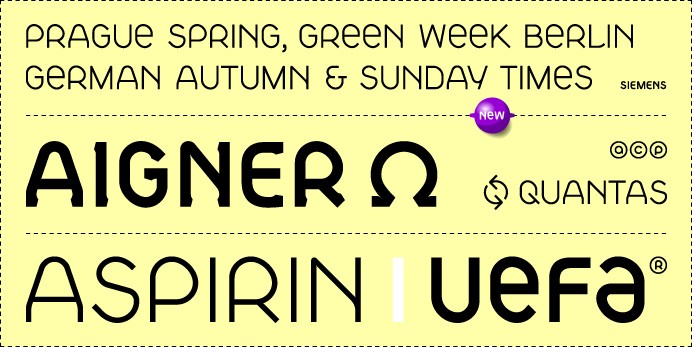
Serifenschriftarten für Bewerbung - ähnlich wie Helvetica!?
ich bin auf der suche nach einer Modernen, schönen und schlichten Serifenschriftart.
Zurzeit verwende ich Helvetica für meine Bewerbungen, nun gab mir aber jemand einen Rat ich sollte doch besser Serifenschriftarten nehmen da diese besser im Fließtext zu lesen seien.
Habe mich gestern Abend schon auf die suche danach gemacht, bin aber leider nicht wirklich fündig geworden, daher hoffe ich das Ihr mir evtl. weiterhelfen könnt.
Hier nochmal die Schriftarten die ich zur Zeit für meine Bewerbung nutze:
Logo,Kopfzeile: Halunken Bold
Rest der Bewerbung: HelveticaNeueLTStd
Würdet ihr die Schriftart passen zu der Halunken Bold (Logo/Kopfzeile) nehmen oder wäre was anderes auch in Ordnung?
Dir ist schon klar, das "Serifenschrift, ähnlich wie Helvetica" schon ein Widerspruch in sich ist.
Helvetica - auch die Helvetica Neue sind eben gerade keine Serifenschriften, sondern eben serifenlose Linearantiqua, also im gegensatz zu den dir empfohlenen Serifenschriften eben KEINE deutlichen Strichstärkenkontraste und KEINE Serifen.
Ja, es war mir schon bewusst das Helvetica keine Serifenschrift ist.
Ich hatte diese nur immer vorher für meine Bewerbungen benutzt da ich sie vom Stil her sehr schön und ansprechend fand.
Habe den Thread hier erstellt da ich dafür eine Alternative Serifenschrift finden möchte.
Wenn ich SkyTypo richtig verstanden habe, sucht er keinen Partner zur Helvetica, sondern einen serifenbehangenen Partner zur Halunken Bold.
Okay. Im Ernst: Ich würde zu dieser doch eher extrovertierten Schauschrift eine schlichte, zurückhaltende Antiqua, Slab oder auch Grotesk wählen. Zum Beispiel:
1. Antiqua
· Lyon
2. Slab
· The Serif
3. Grotesk
· Avenir
Edit: Oder man sucht auch hier den formalen Zusammenhang.
• T-Star
• DIN Slab
Ich würde die Halunken sehr viel eher auswechseln als die Helvetica! Es hängt zwar immer von der Branche ab, aber in den meisten Personalabteilungen dürfte diese Schrift für mindestens eine hochgezogene Augenbraue sorgen, und ich wage zu bezweifeln, dass dies in jedem Fall ein günstiges Zeichen wäre. Im Ernst: Mit dieser eigenwilligen Schrift würde ich meine Bewerbung nur dann bestücken, wenn ich sie selber entworfen hätte und mich bei einer Foundry bewerbe …
Wenn es nicht die Bewerbungsschriftenklassiker Helvetica und Times sein sollen, dann würde ich eher auf eine aufeinander abgestimmte Kombination gehen wie Minion/Myriad, Gandhi Sans und Serif oder, wenn es etwas exklusiver sein soll, Lemon Sans und Serif oder die Marat-Familie.
Vielleicht wäre die Liste für wissenschaftliche Arbeiten gar kein schlechter Anhalt, weil hier immer gleich passende Paare aus Sans und Serif vorgeschlagen werden.
Nochmal im Ernst: Es kommt eben auch darauf an, um welche Branche es sich handelt. Generell ausschließen würde ich diesen Font nicht (auch wenn er mich persönlich nicht vom Hocker haut).
An der Halunken Bold ist leider nicht mehr soviel zu rütteln, ist wie gesagt auch nur ein kleiner Teil der Bewerbung der mit dieser Schriftart ist (Kopfzeile - eine Art Briefpapier von mir selber entworfen, wenn man so will). Bisher kamen meine Bewerbungen auch gut bei den Personalern an. Wie Thomas Kunz schon richtig erwähnt hatte suche ich einen "serifenbehangenen Partner zur Halunken Bold". Sowie R::bert schon in dem zitierten Post ebenfalls gesagt hat, wäre es glaube ich am besten, wenn mann die Halunken-Schriftart mit einer "schlichte, zurückhaltende Antiqua, Slab oder auch Grotesk" kombinieren würde.
Ich Bewerbe mich in relativ Unterschiedlichen Branchen, daher bräuchte ich wahrscheinlich eher was allgemeines, eine Schriftart/Schriftstil die man für alle Bewerbungen verwenden kann.
Ja, es geht um eine Bewerbung für eine Lehrstelle.
Dann kann ich Dir nur den guten Ratschlag meiner geschätzten Kollegin Kathrin ans Herz legen.  :nicken:
Und falls Dir die Auswahl der in ihrer Liste vorgeschlagenen Sippen nicht ausreicht, findest Du hier weitere Vertreter gut ausgebauter Großfamilien:
Schriftfamilien mit mindestens drei Stilen